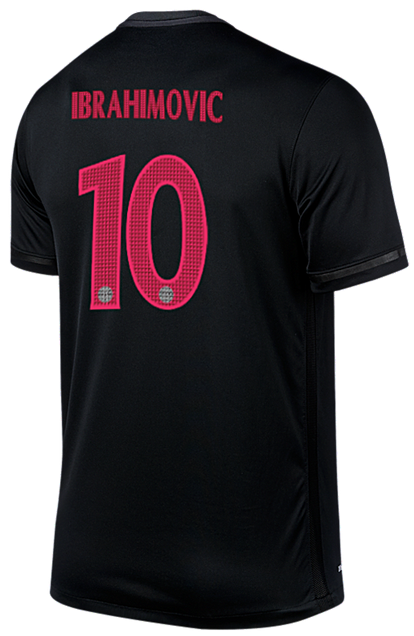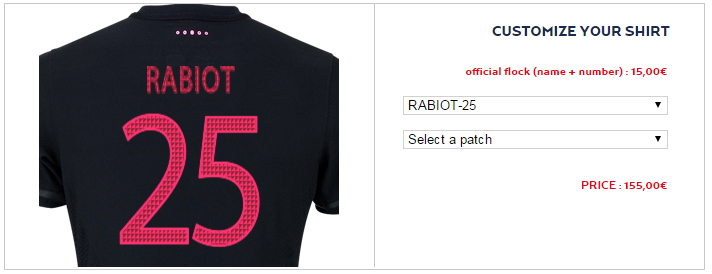
先日発表になったパリ・サンジェルマンの新しいサードユニフォーム。
クラブエンブレムも黒と白になるなど黒を基調としたモノトーンな仕上がりはかなりクールだ。
さて、この新サードユニのフォントカラーがピンクであることが判明した。NIKEやクラブの公式オンラインショップで確認することができる。
黒×ピンクのカラーリングはかなり目立つ!そして、よく見るとエンブレム同様にフォントや背番号にも鱗文様が取り入れられているようだ。